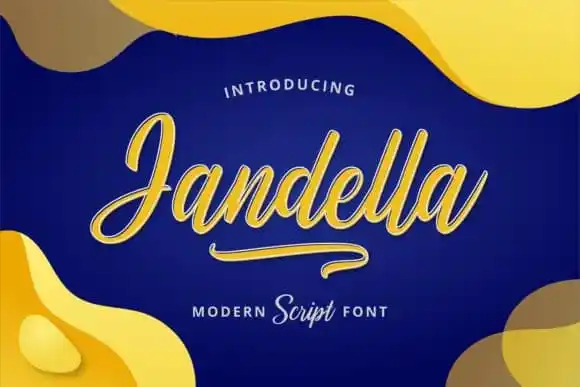
Jandella Script Font – Download Grátis
A Jandella Script Font é uma variedade única de garras cursivas que foram atualizadas para uma versão mais sofisticada e elegante. Ela incorporou elementos de fantasia e rascunho feito a mão, resultando em uma tipografia divertida e incrivelmente graciosa. Esta fonte foi projetada e compartilhada pela brithostype, que a apresenta como um estilo refinado e altamente sofisticado. Suas linhas delicadas se encaixam perfeitamente em eventos festivos como cartões de casamento, cartões de agradecimento, citações e carteiras de dívidas. Ela também faz uma pausa maravilhosa em oásis criativos, como logotipos, cartões de visita e qualquer outro projeto que pode beneficiar do toque refinado dos rascunhos feitos a mão.